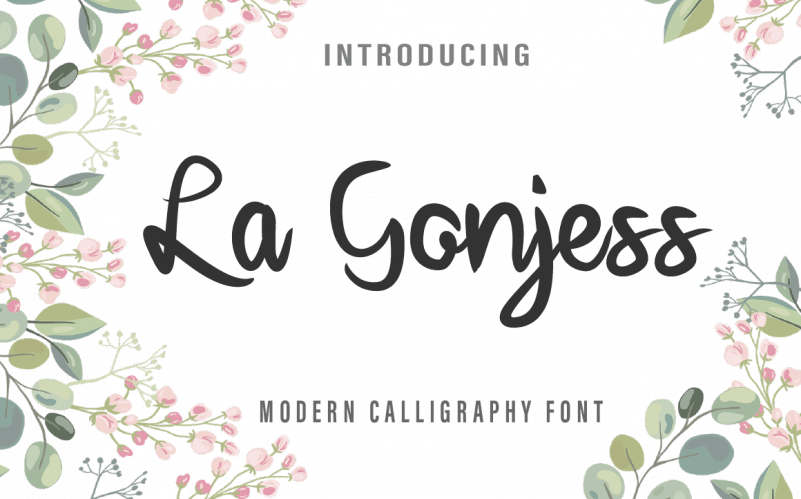
La Gonjess Script Font – Download Grátis
La Gonjess Script é uma elegante fonte cursiva criada por Farz Studio que transmite emoções suaves e encantadoras através das letras. Desenhadas com um toque de originalidade, as formas redondas desta fonte permitem criar arte exuberante em estilo gávia. Suas letras divertidas e fluidas tornam La Gonjess Script uma escolha perfeita para aqueles que desejam imprimir vida nos seus projetos. Seja você um designer de site ou gráfico, adicionando esta linda fonte à sua coleção é a maneira ideal de transformar suas criações em algo único e encantador.